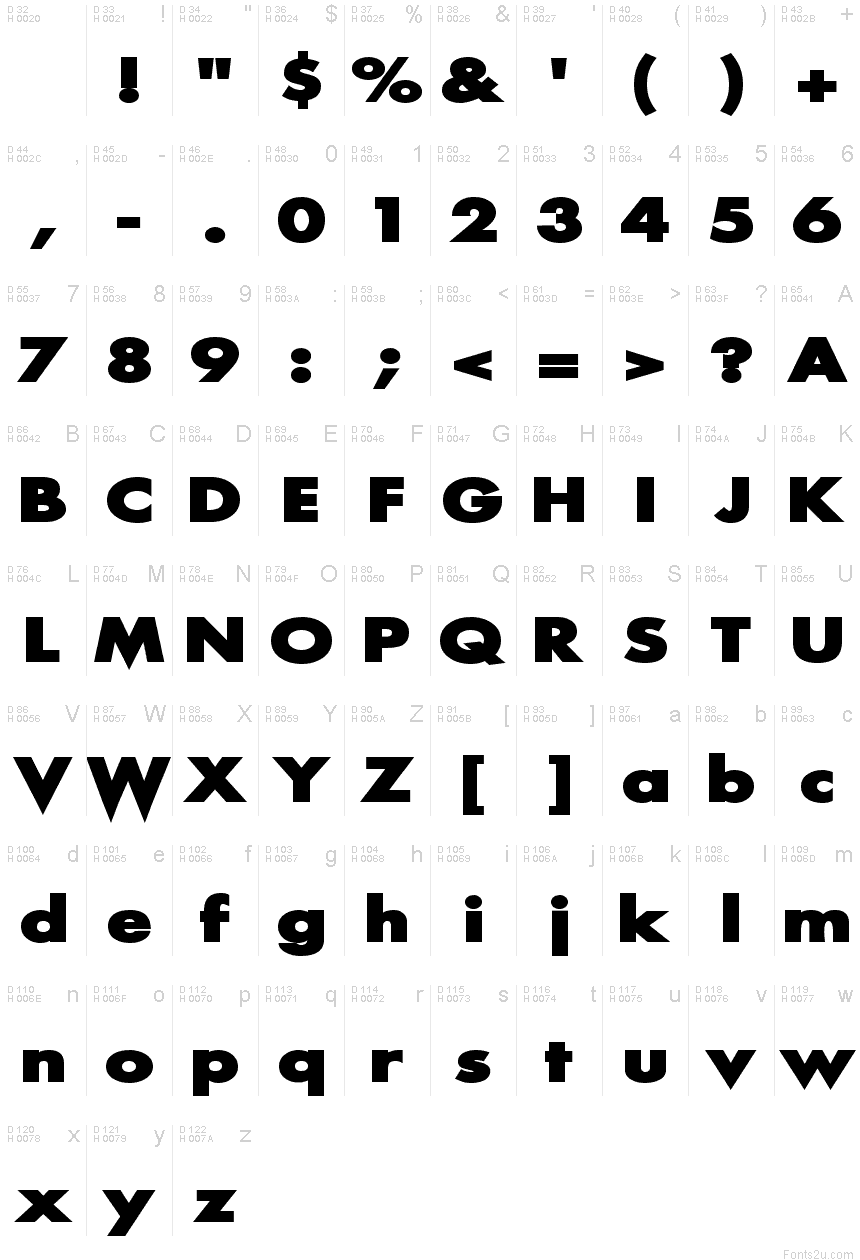
Scream, die kostenlose Horror-Logo-Sans-Serif von Samuel Park, orientiert sich am Schriftzug der Scream-Filme von 1999 und verwandelt eine wuchtige, abgerundete Schrift in ein spannungsgeladenes, filmreifes Statement. Die Buchstaben wirken stumpf und kompakt, werden dann aber plötzlich durch scharfe Schnitte und flache Kanten aufgebrochen. So erhält die Schrift diesen vertrauten Thriller-Look der späten 90er, ohne dabei wie eine billige Spielerei zu wirken.
Sie eignet sich perfekt für Filmposter, DVD-Cover, Halloween-Flyer, Streaming-Thumbnails und Merch-Grafiken – überall dort, wo kurze Worte den richtigen Film-Vibe brauchen. Als Freefont entfaltet die Schrift ihre Wirkung am besten im Display-Bereich: Dank der kräftigen Formen und der abrupten Schnitte verleiht sie selbst einfachsten Begriffen diesen abgehackten, spannungsvollen Charakter eines professionellen Horror-Logos.
Based on the Scream films logo. Samuel Park -99
Scream